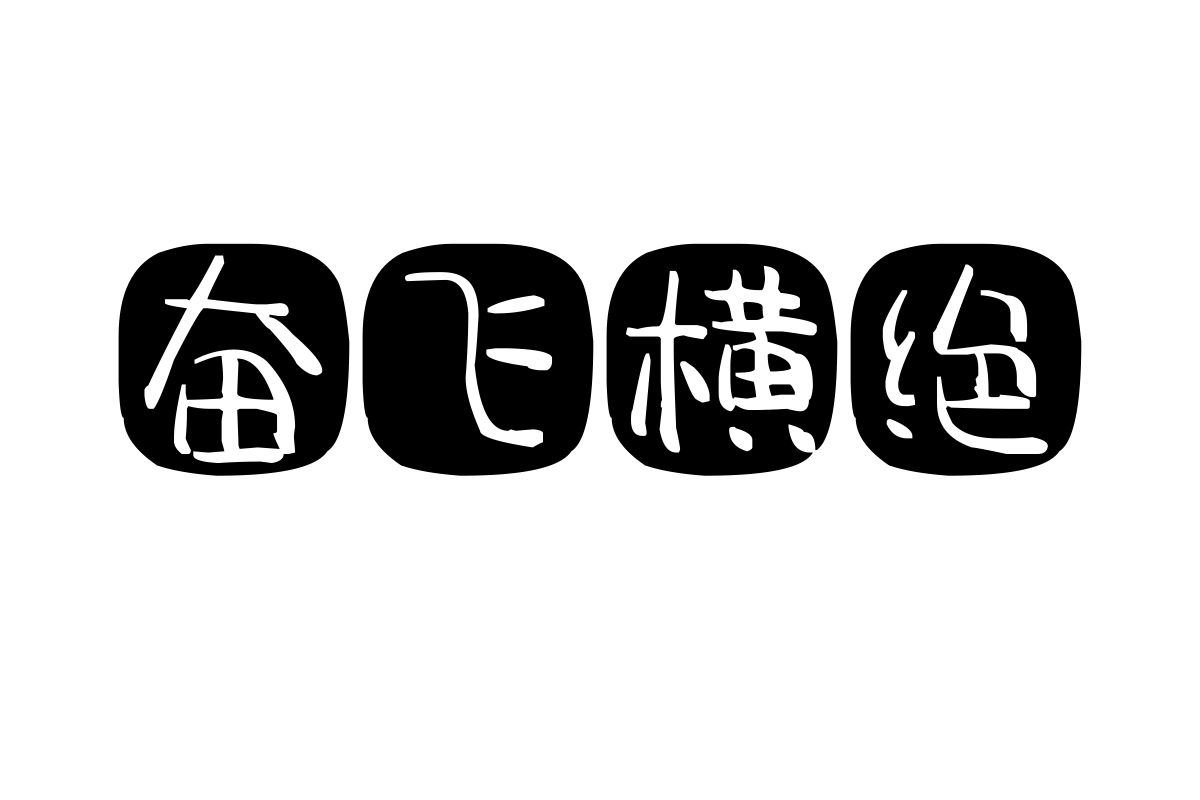
蝉羽青城坨坨体是一种独特的书法字体,由书法家张涛在2019年创作。这种字体以蝉翼般的线条和青城山的形态为灵感,具有很高的艺术价值和观赏性。
蝉羽青城坨坨体的特点是笔画流畅、线条柔美,给人一种轻盈飘逸的感觉。字体结构紧凑,字形大小适中,易于阅读。同时,这种字体还融入了中国传统书法的元素,如篆刻、隶书等,展现了深厚的文化底蕴。
总的来说,蝉羽青城坨坨体是一种极具艺术魅力和观赏价值的字体,适合用于书籍、杂志、广告等场合的标题和正文。